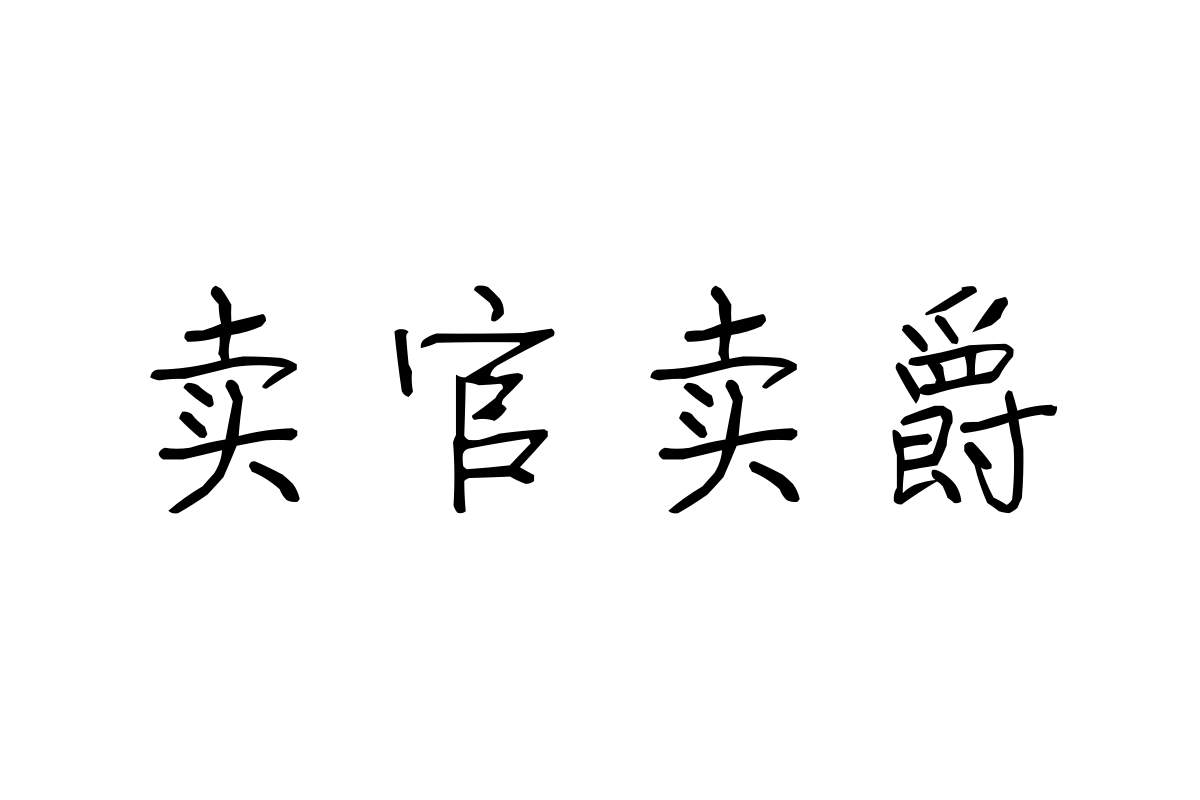
三极子偕行楷字体是一种具有独特风格的汉字书写风格,它结合了楷书的规范性和行书的流畅性。这种字体的特点是笔画粗细变化明显,结构紧凑,线条清晰有力,给人一种强烈的视觉冲击感。
在三极子偕行楷字体中,每个字的笔画都有明确的起止点和转折,使得整个字形看起来更加规整和易于识别。同时,这种字体也注重笔画之间的连接和过渡,使得整体字形显得更加连贯和自然。
三极子偕行楷字体的特点在于其独特的结构和笔画处理方式,使得它在保持楷书规范性的同时,又具备了行书的流畅性和艺术性。这种字体适合用于各种需要清晰、易读的场合,如书籍、报纸、广告等。